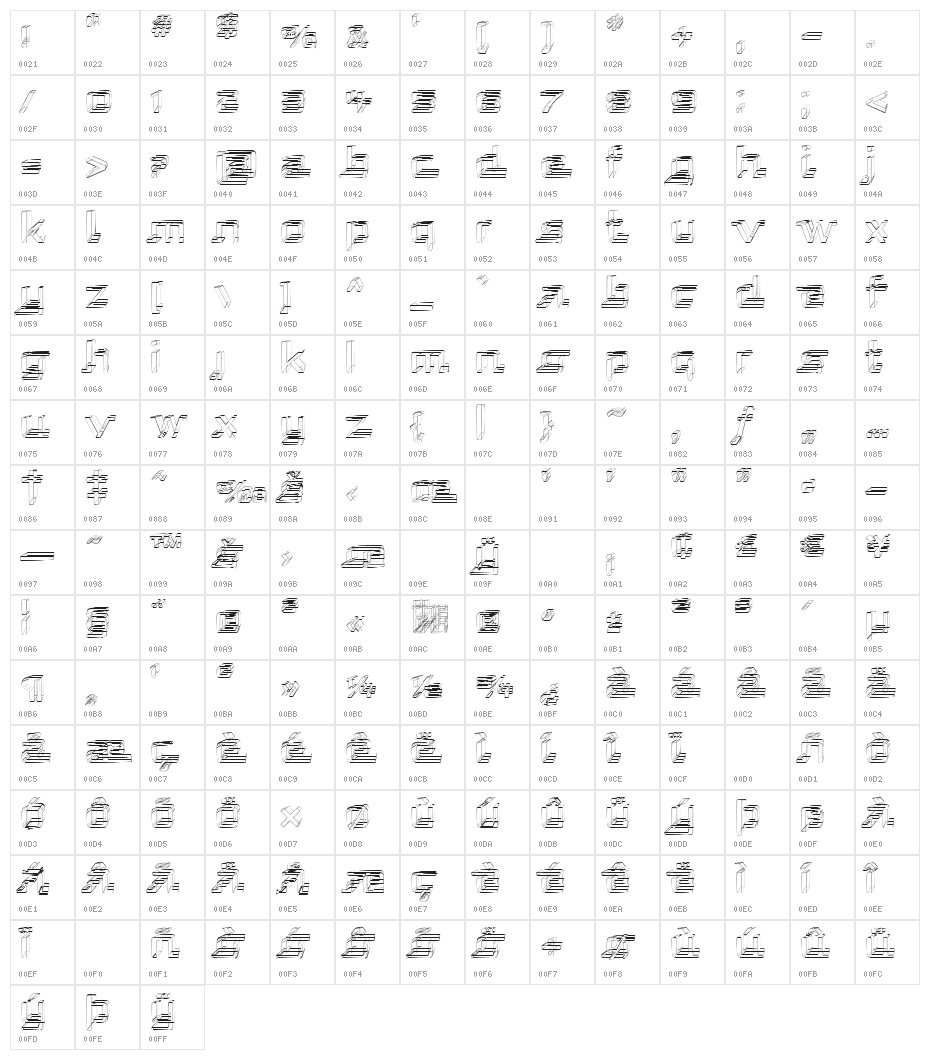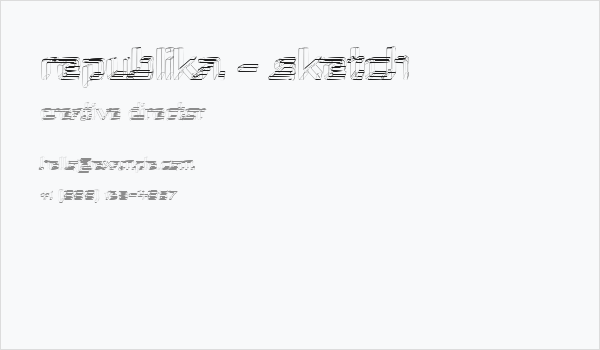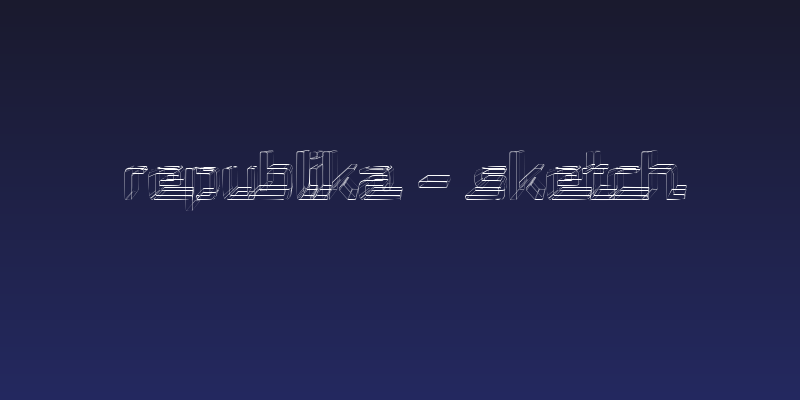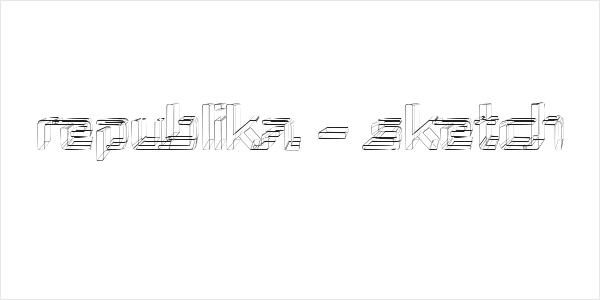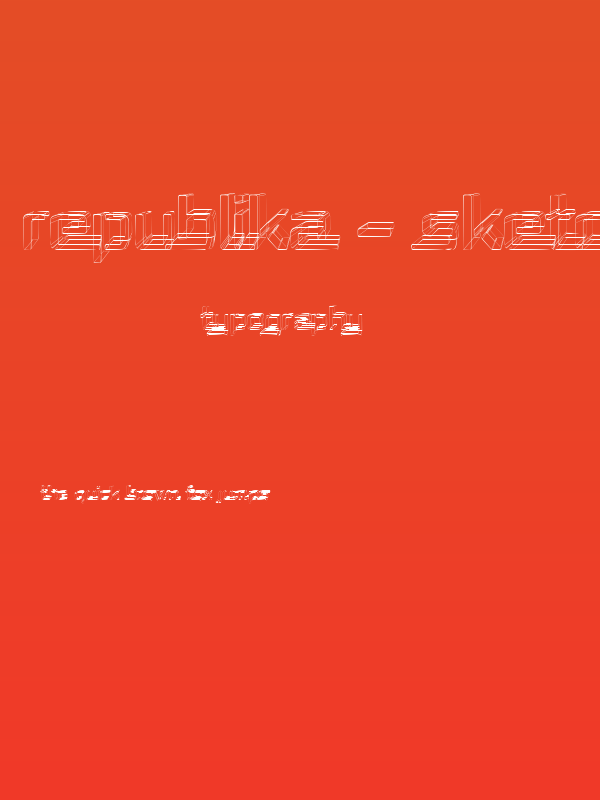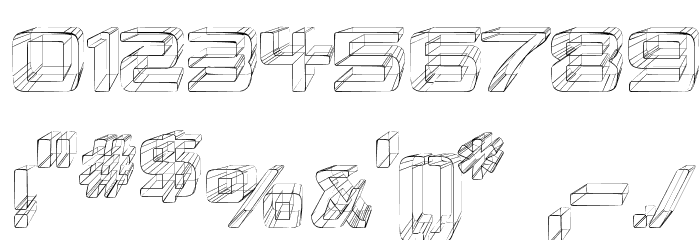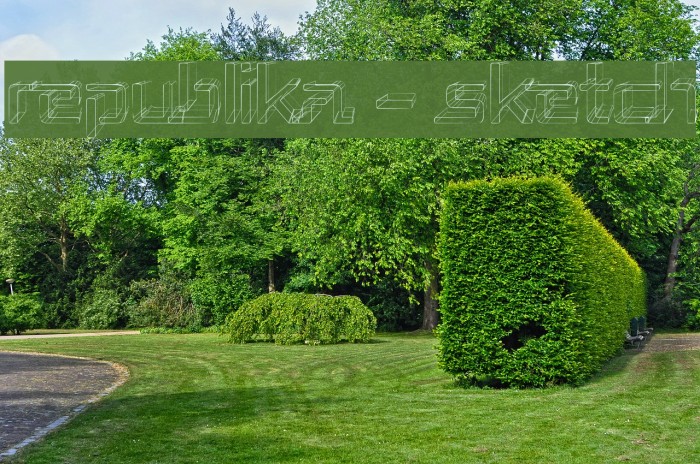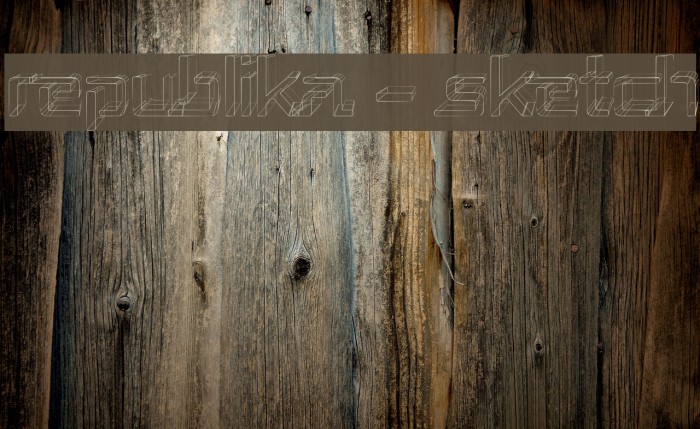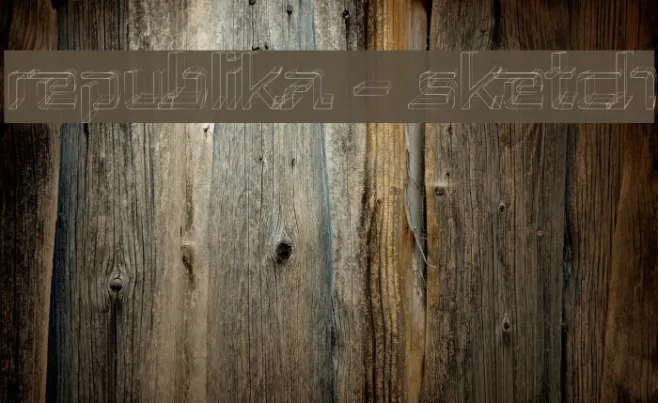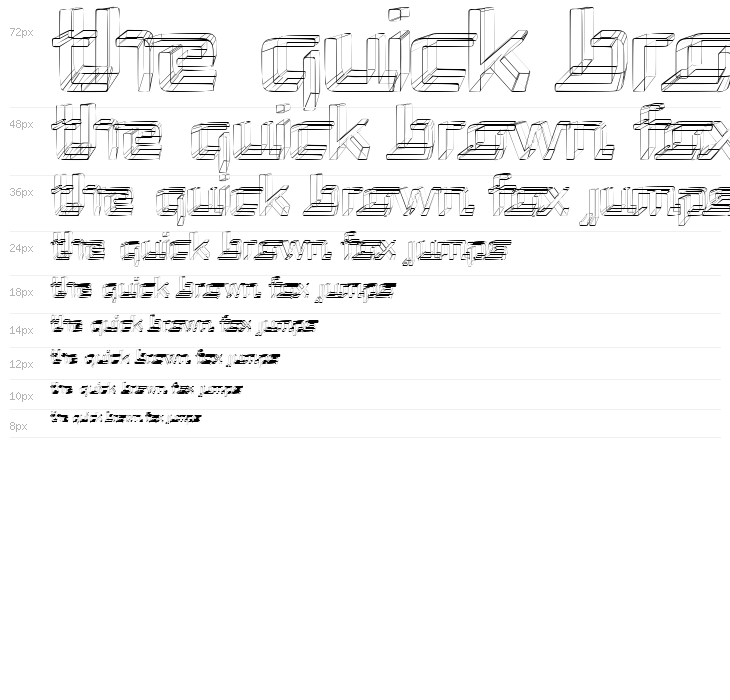
Republika - Sketch Font
| Style général | Modern, Artistic |
| Cas d'utilisation | Headlines, Logos, Artistic projects |
| Projets proposés | Ideal for creative projects such as posters, album covers, or branding materials where a unique and artistic touch is desired. |